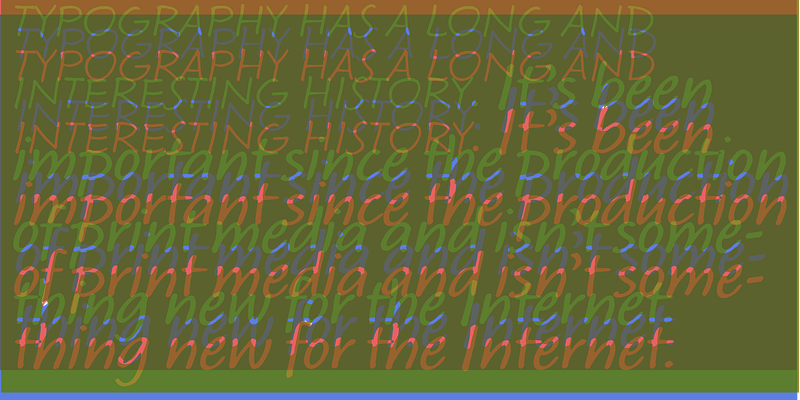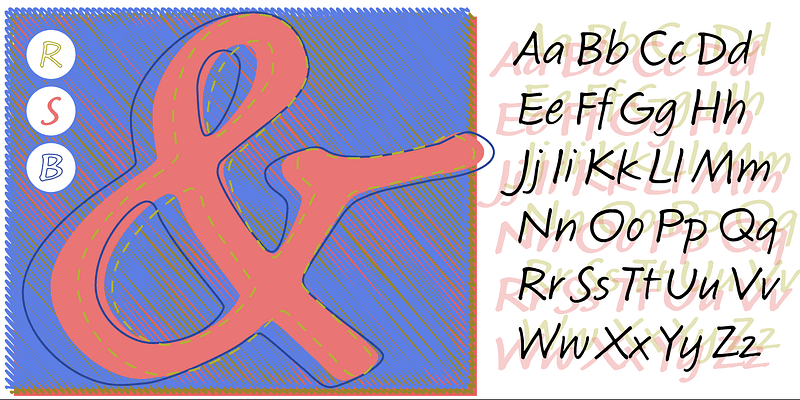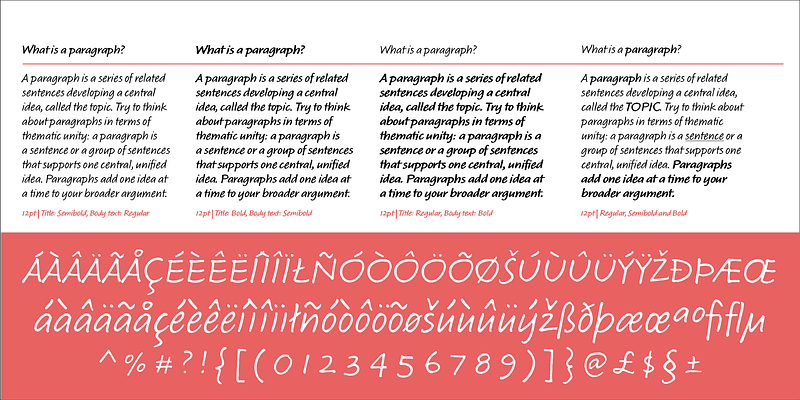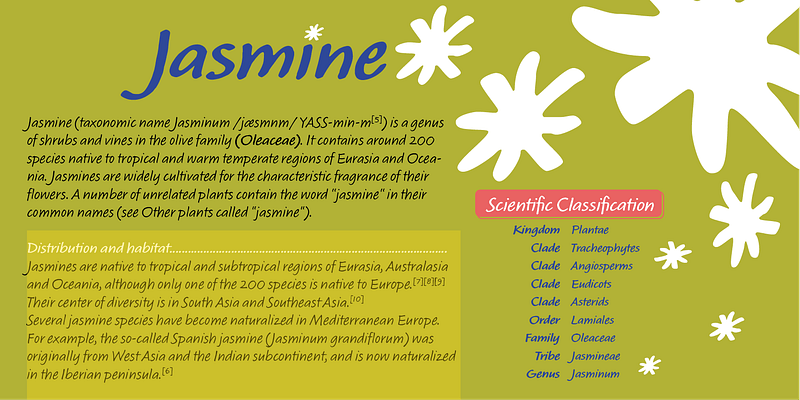
Gayle Sato, amie de longue date de MVB Fonts, a une écriture incroyable. C’est une écriture naturelle, simple, au rythme parfait. Dépourvue de fioritures, elle ne cherche pas à être belle. Elle est simplement authentique, rapide et propre ; l’écriture que nous aimerions tous avoir. La numérisation de Mark van Bronkhorst capture ces qualités. En conservant la rugosité d’un feutre, MVB Calliope est une police d’écriture beaucoup plus authentique que la plupart des autres, très lisible mais toujours brute. Le Regular est sorti en 2005, avec les autres graisses peu de temps après.
MVB Fonts est une fonderie numérique créée en 1991 par le concepteur de polices Mark van Bronkhorst ayant son siège social dans la baie de San Francisco.